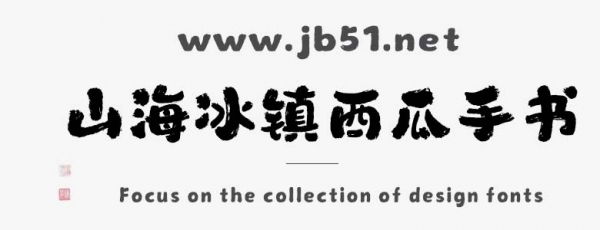
山海冰鎮(zhèn)西瓜手書W是由山海字庫(kù)出品的字體,這款字體筆觸略粗,具有很好的視覺(jué)感,適合應(yīng)用于藝術(shù)設(shè)計(jì)、平面宣傳設(shè)計(jì)、網(wǎng)頁(yè)設(shè)計(jì),書法字帖等領(lǐng)域,需要的朋友可以前來(lái)本站下載。